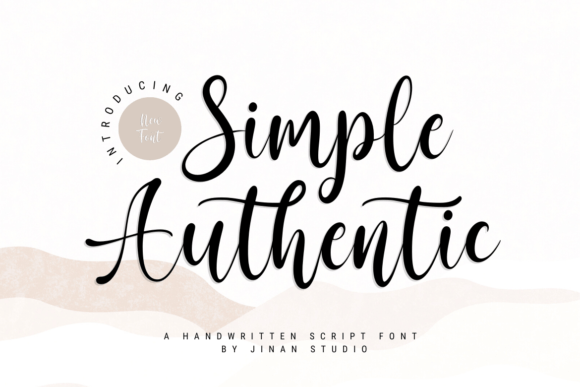
Simple Authentic
Mencari elemen desain yang tepat bisa jadi sulit, namun Simple Authentic menawarkan koleksi luar biasa yang akan langsung meningkatkan kualitas karya Anda.
Baik Anda membuat produk POD (Print on Demand), undangan pernikahan, atau grafis media sosial, Simple Authentic adalah pilihan yang sangat ideal.